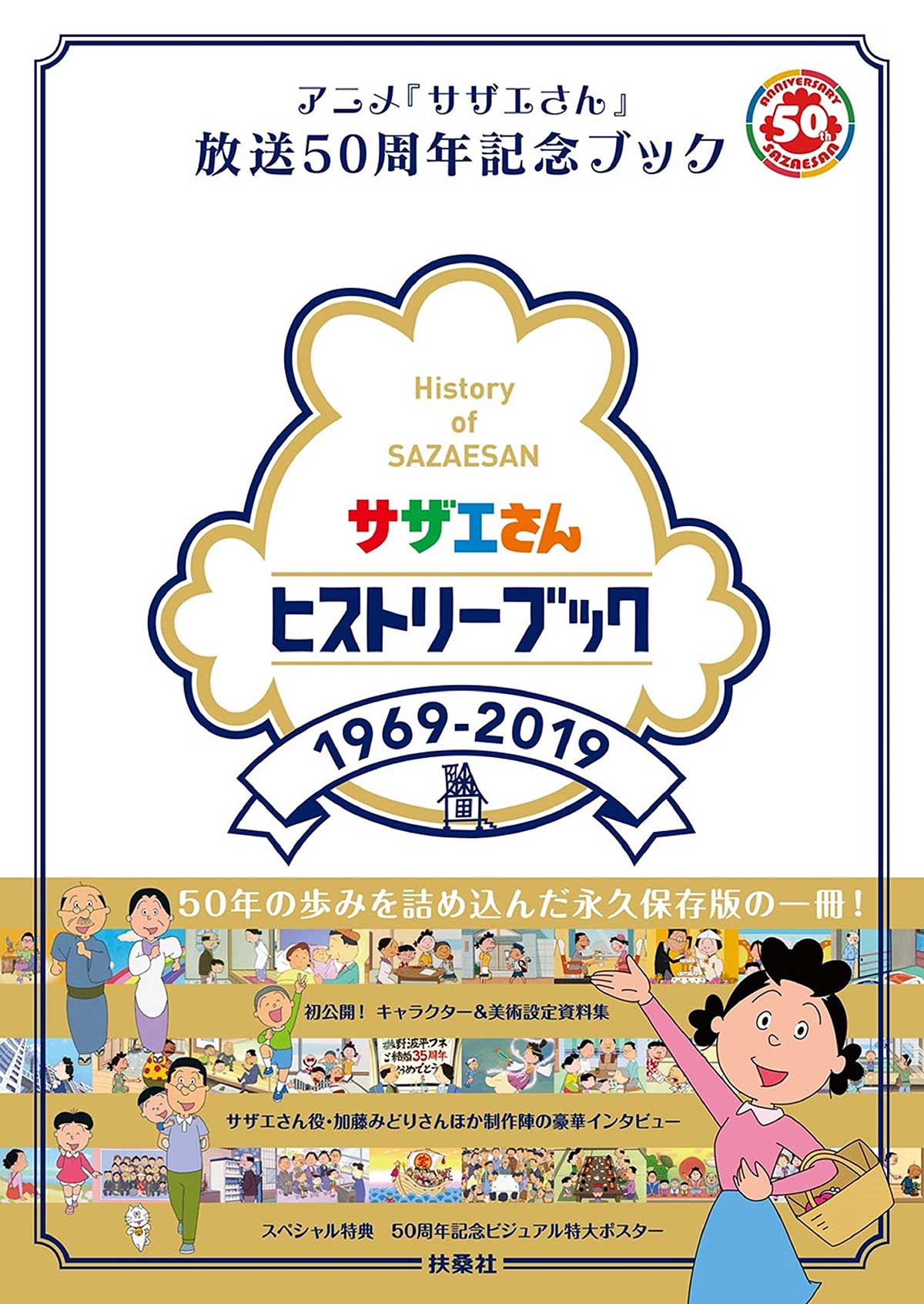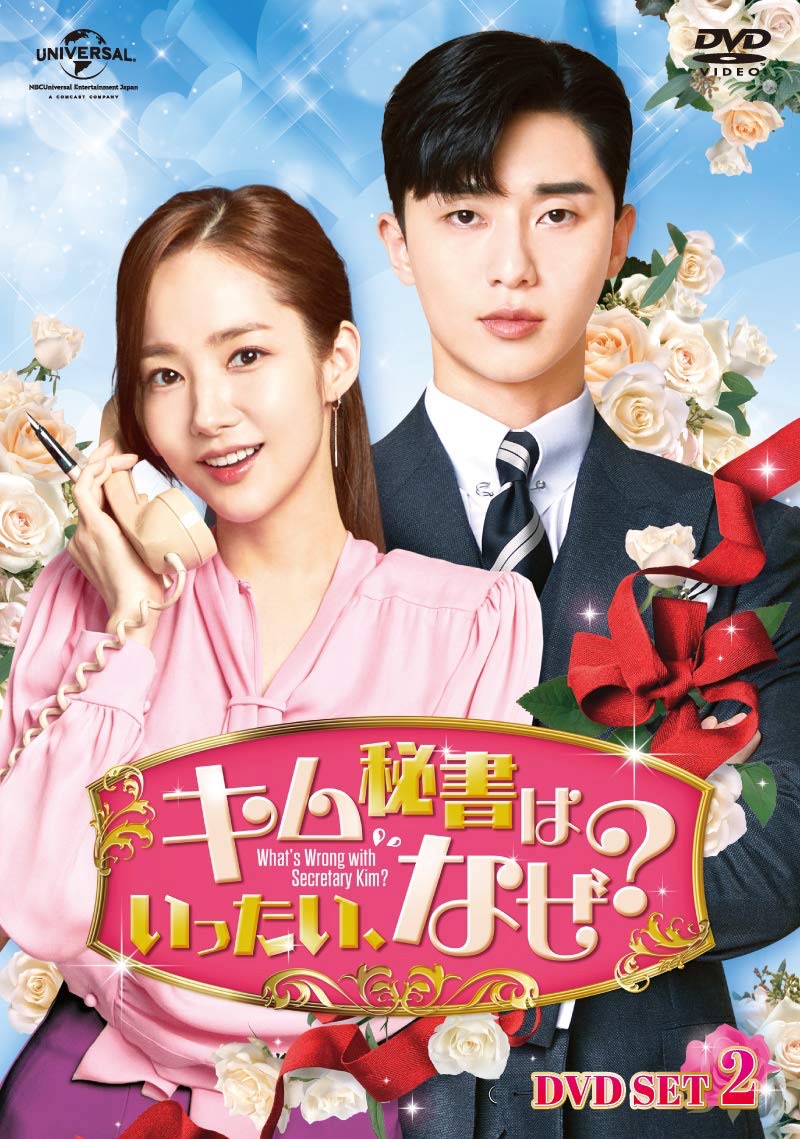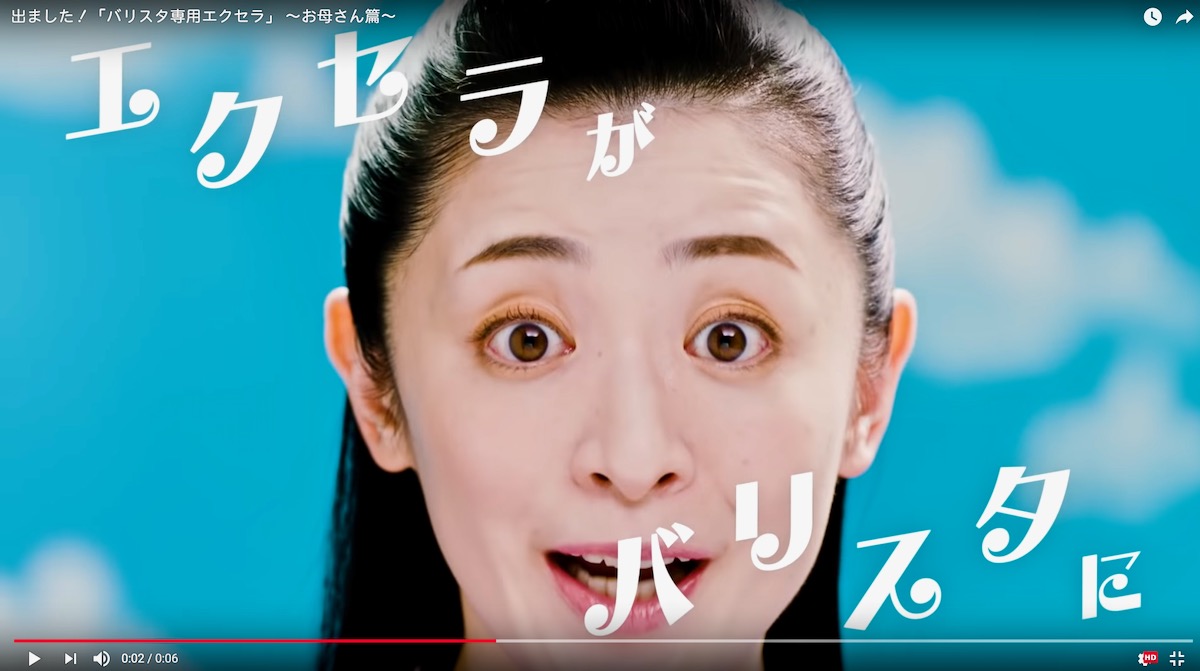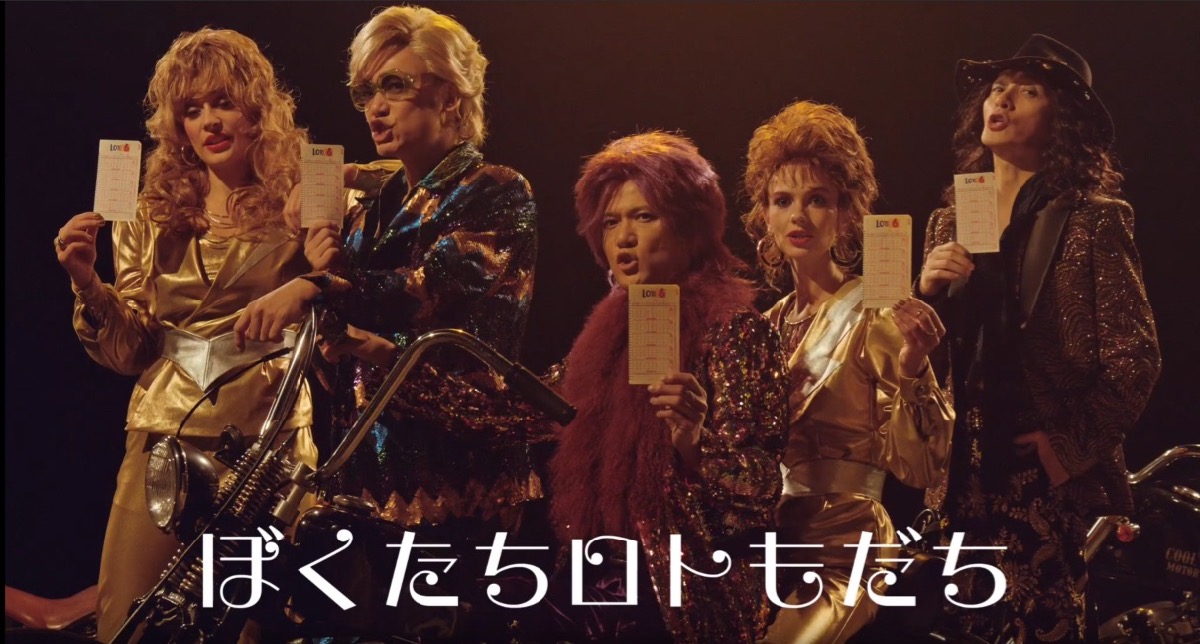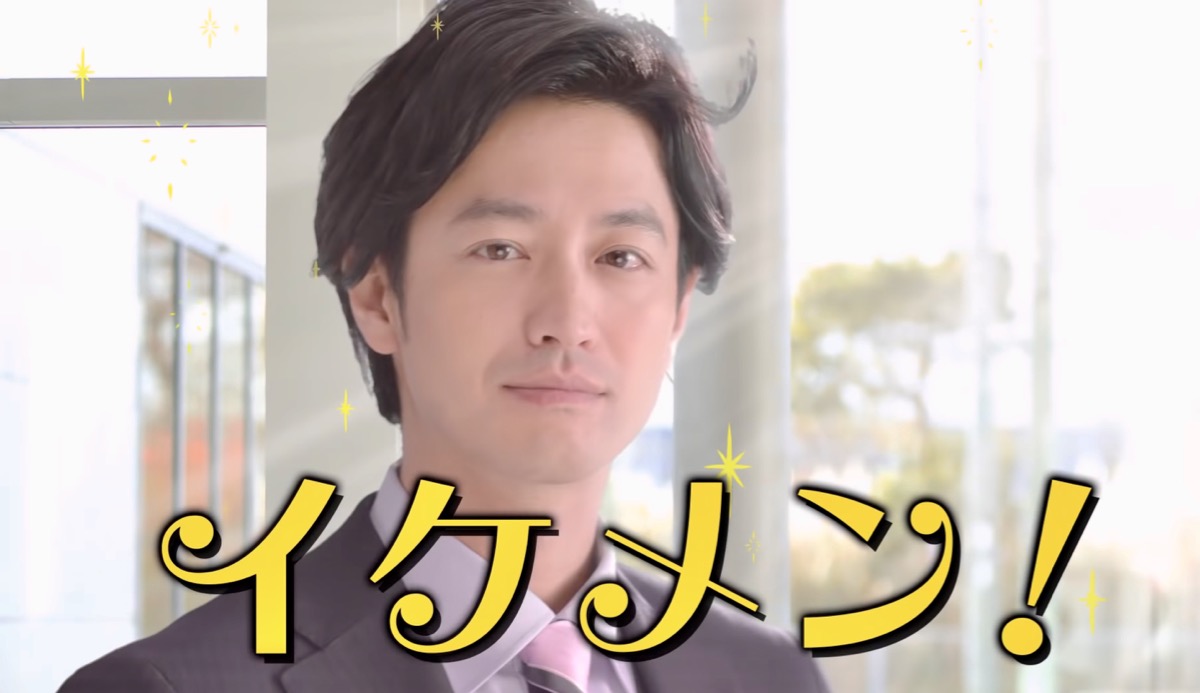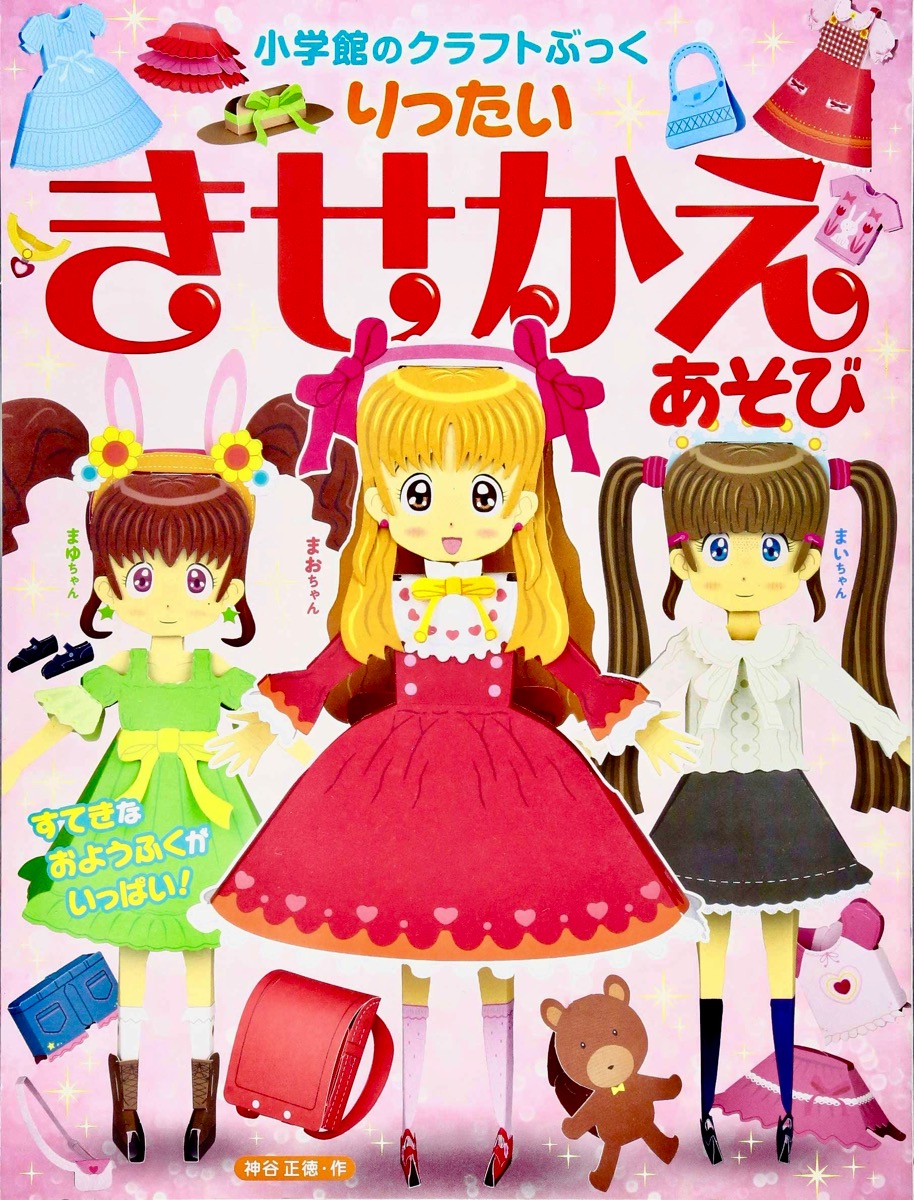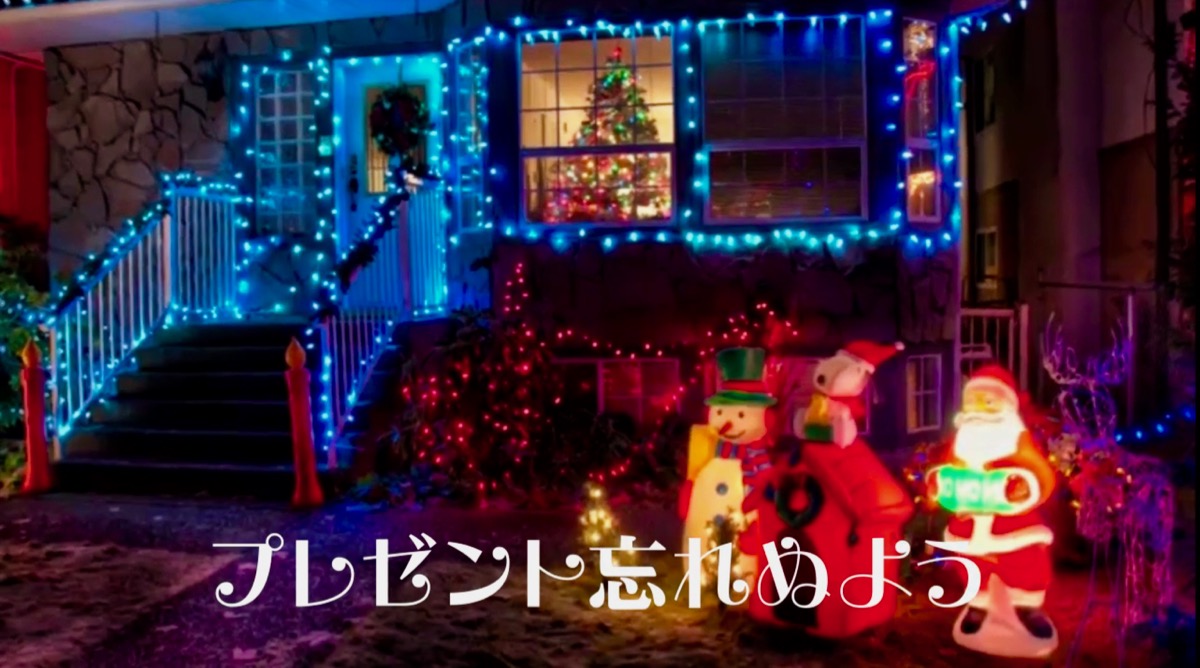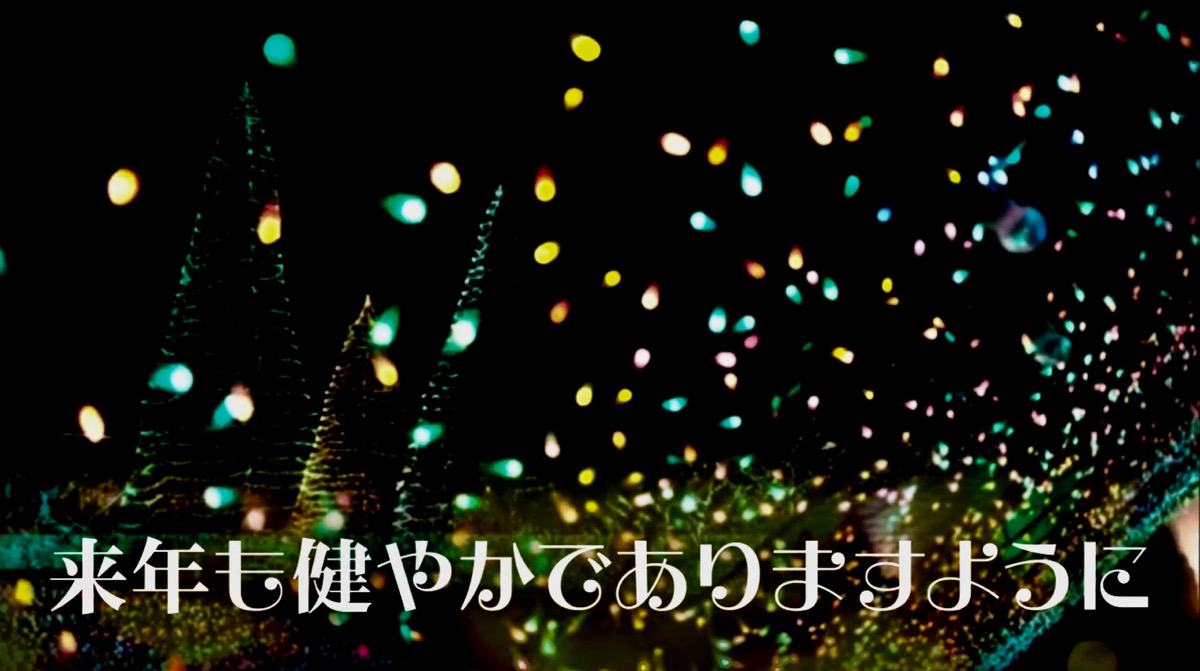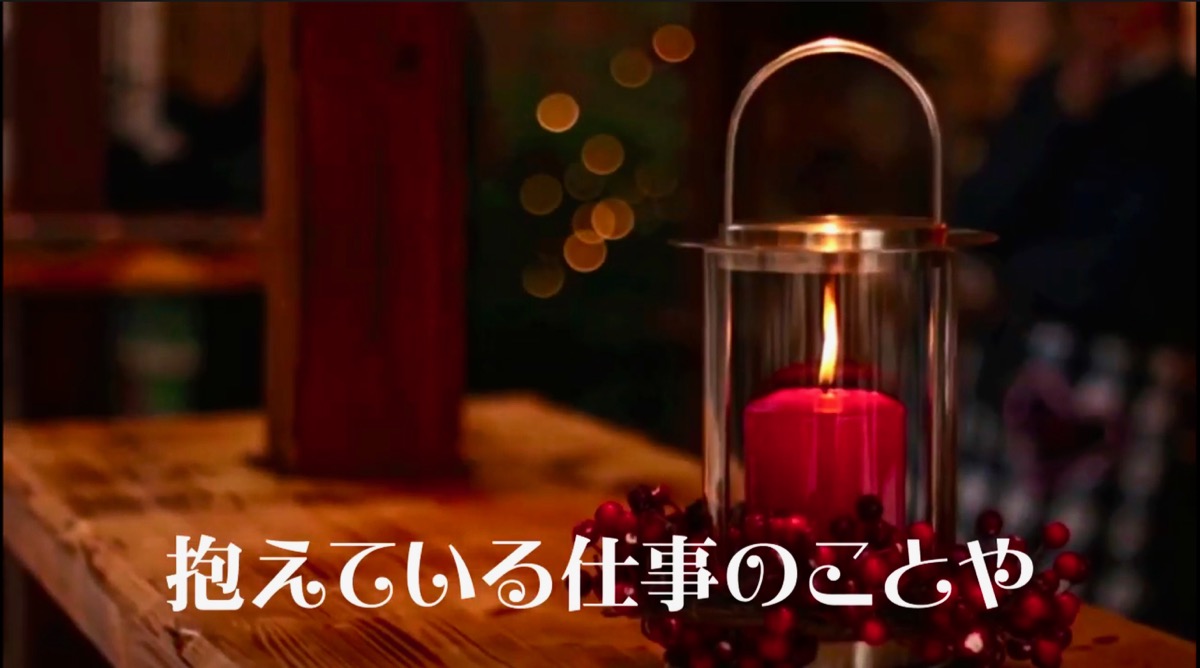
テレビ番組  さとうゆたか  2021年2月27日(土) 16:11
日本テレビ「ヒルナンデス」。
本の表紙  さとうゆたか  2021年2月15日(月) 14:46
書名:人外サーカス
著者:小林 泰三
発行:KADOKAWA
シール絵本  さとうゆたか  2021年2月7日(日) 8:45
書名:スイーツパーティー シールあそび
著者:講談社
発行:講談社
本の表紙  さとうゆたか  2021年1月25日(月) 8:44
書名:ラッキーになれる習慣
著者:武田双雲
発行:清流出版
とびだす!どうわ  さとうゆたか  2020年12月19日(土) 16:14
書名:ねむれるもりのびじょ
著者:スザンナ・デイヴィッドソン、ジョージ・エルモス
発行:大日本絵画
さとうゆたか  2021年1月3日(日) 9:30 [修正]
これも同じシリーズかな。
書名:しらゆきひめ
著者:スザンナ・デイヴィッドソン
発行:大日本絵画
キャンペーンロゴ  さとうゆたか  2020年11月12日(木) 8:59
ショッピングセンター内のレストラン街。
テレビ番組  さとうゆたか  2020年11月7日(土) 16:08
日本テレビ「メレンゲの気持ち」だったかな…。
ぬりえブック  さとうゆたか  2020年10月19日(月) 16:33
書名:プリンセスぬりえブック
発行:宝島社
テレビ番組  さとうゆたか  2020年10月9日(金) 15:00
日本テレビ「メレンゲの気持ち」。
「映画プリキュア」公式サイト  takumi  2020年5月7日(木) 22:51  HP
「映画プリキュアミラクルリープ みんなとの不思議な1日」の公式サイトで「えれがんと」書体が使われています。
プリキュア系では、めちゃめちゃ好まれていますね。
takumi  2020年5月7日(木) 22:53  HP [修正]
もう1枚だけ。
「ミラクルンライト」の文字ですね。
1枚目の画像みたいな使い方も良いですが、こういう少ない数の文字を大きく、シンプルに決めた方が映えると思います。
さとうゆたか  2020年5月8日(金) 8:32 [修正]
さとうゆたか  2020年9月27日(日) 16:39 [修正]
映画館に貼られていたポスターです。